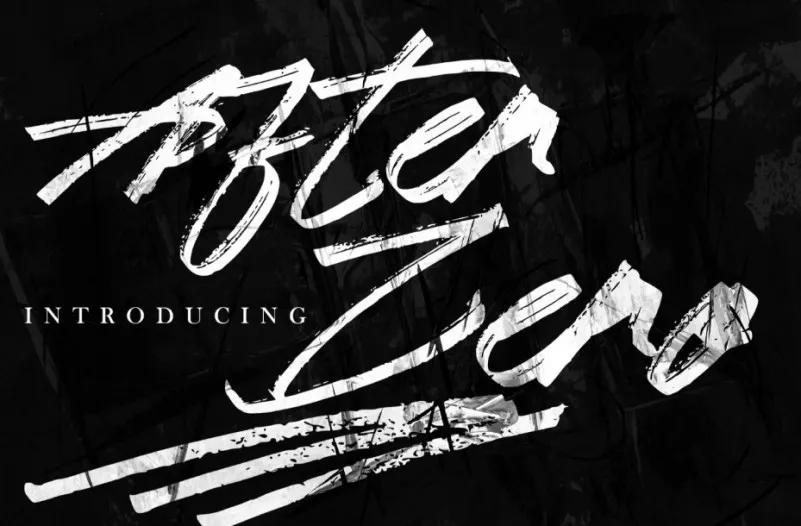
Descubra “After Zero Font”, uma nova tipografia moderna que traz a arte do swiping para os projetos digitais. Este ‘Script Fonts’ foi criado pelo designer Hamilton, combinando elegância e poder ao mesmo tempo. Com seu estilo de caligrafia artesanal, esta fonte é perfeita para aqueles buscando uma identidade visual única e inovadora. Ideal tanto para projetos promocionais que incluem cartazes, flyers ou materiais em formato digital quanto para manusear mensagens escritas a mão e até mesmo para produtos de embalagem e marcas corporativas. A “After Zero Font” é uma opção versátil que pode transformar qualquer projeto de design em destaque. Seja você um designer gráfico experiente ou iniciante, este swivel script font definitivamente merece sua atenção. Não hesite mais, ele trará seu trabalho para o topo do catálogo.